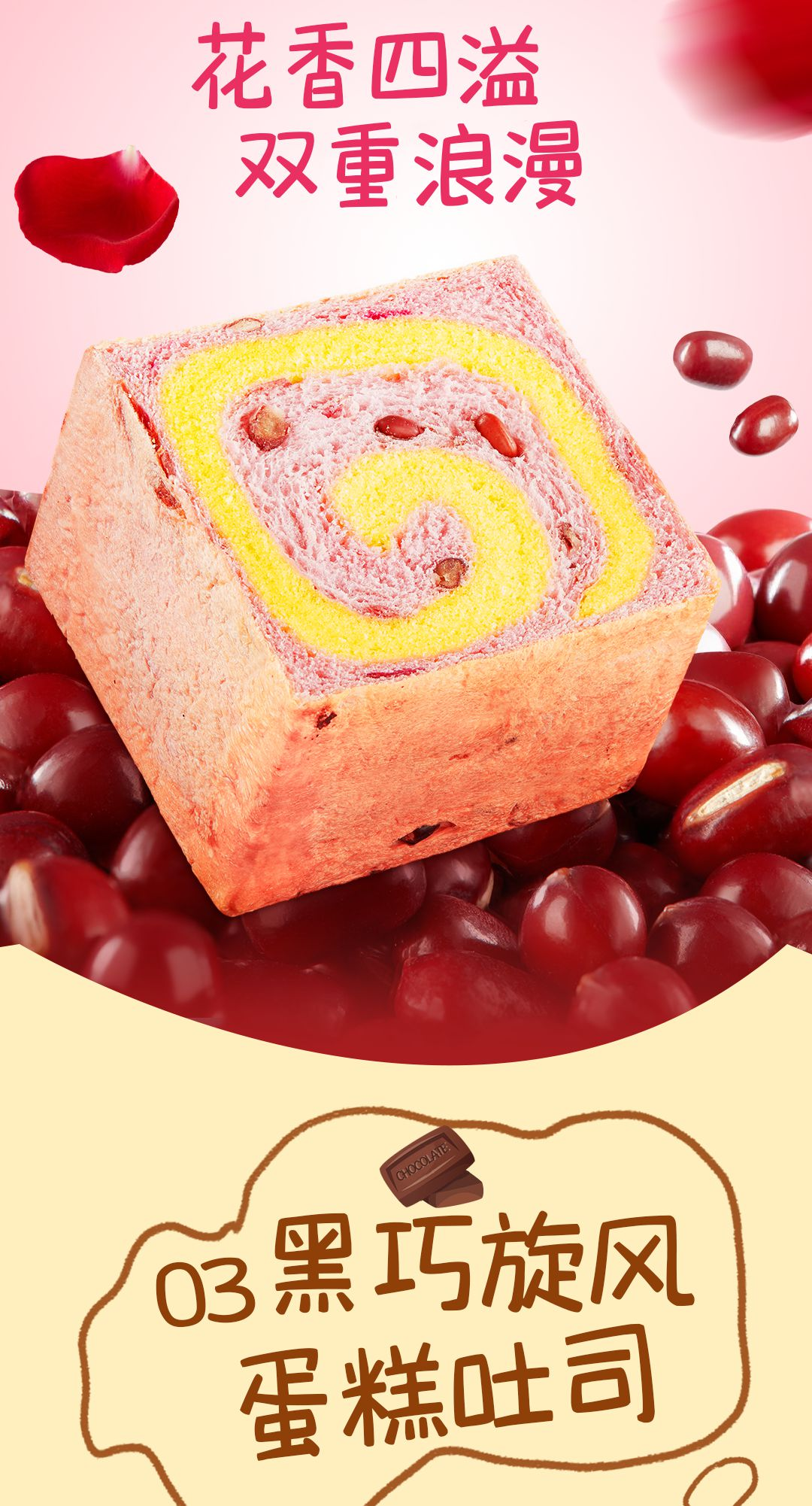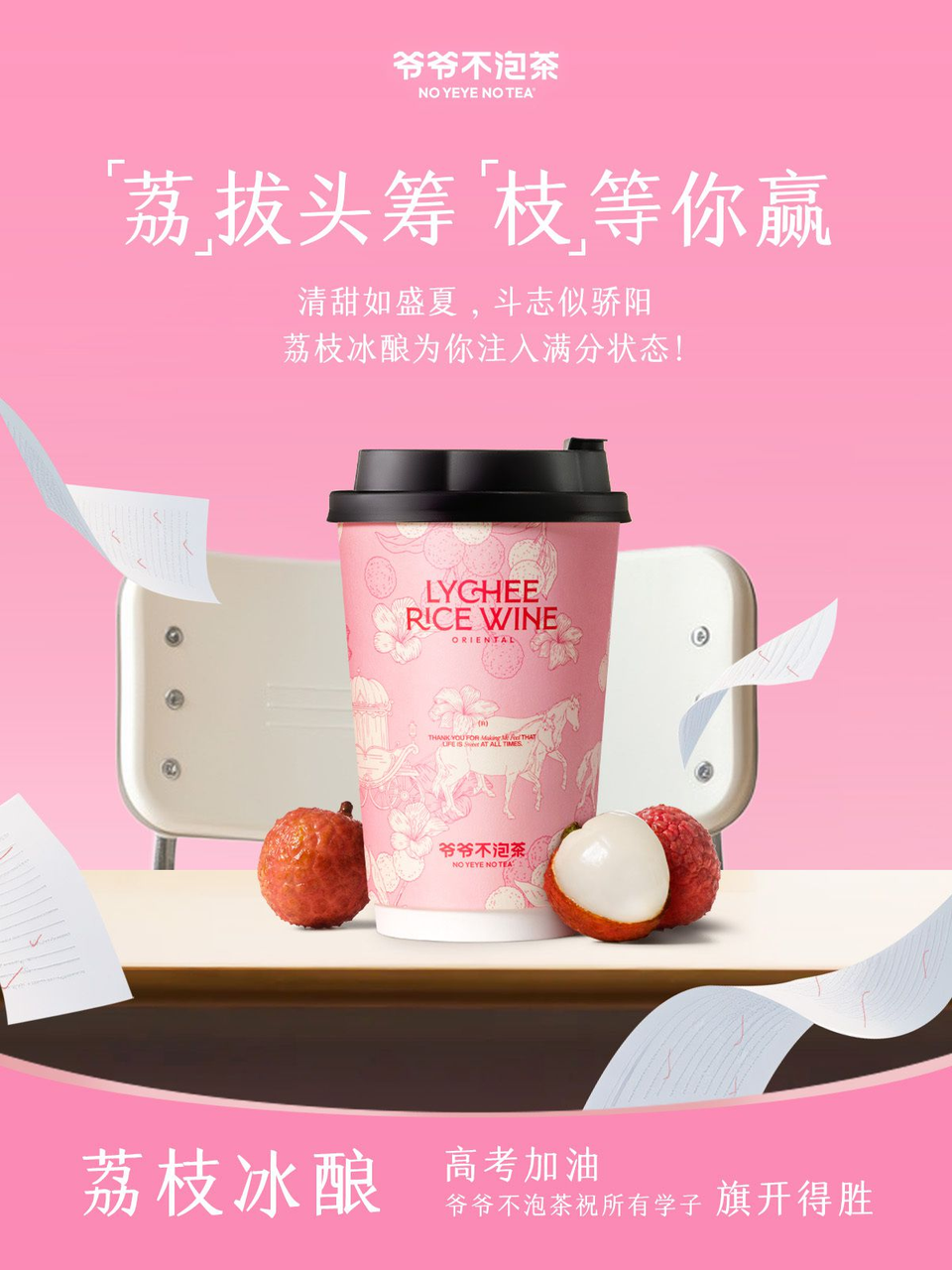
怎么找适合海报的字体?一套方法帮你快速定位
做海报时最让人头疼的问题之一,就是“该用什么字体”。打开字体列表,几百款字体摆在眼前,翻来翻去却不知道选哪个。其实,找对字体并不靠运气,掌握一套方法,就能快速缩小范围、精准定位。
一、先搞清楚:你的海报在“说”什么?
选字体之前,先问自己三个问题:
海报的主题是什么? 是促销活动、品牌宣传、音乐会,还是公益公告?不同主题对字体的要求完全不同。音乐节海报可以用夸张的装饰体,金融讲座海报则需要稳重专业的字体。
目标受众是谁? 年轻人喜欢潮酷、有个性的字体;儿童相关的设计需要圆润可爱的字体;面向高端商务人群,则要选择精致、有质感的字体。
想传递什么情绪? 高端、活泼、复古、科技、温馨还是严肃?字体的情绪必须与海报的整体氛围一致。
这三个问题明确了,选字体的方向就清晰了一大半。
二、认识字体的“性格”
不同字体自带不同的“性格”,选对了能让海报事半功倍:
黑体/无衬线体:简洁有力、现代感强,视觉上自带冲击力,是海报标题的“第一选择”。粗黑体适合促销、公告等需要强烈视觉冲击的场景;细黑体适合科技、互联网等现代感强的设计。代表字体有思源黑体、阿里巴巴普惠体等。
宋体/衬线体:端庄雅致、精致传统,带有文化感和高级感。适合文化艺术、奢侈品、女性行业等追求精致感的设计。
手写体/书法体:个性强、有温度,但辨识度较弱,建议只用于标题,不要用作正文。儿童用品海报适合灵动的手写体;中国风的设计场景,如传统节日、国潮服饰等,书法体是首选。
圆体/卡通体:亲和活泼,适合儿童、少女、甜品等温馨品类。
装饰体/展示体:造型独特、视觉冲击力强,适合音乐节、潮流活动等需要强烈视觉吸引力的场景。同样只适合做标题,不宜用于正文。
三、搭配原则:少即是多
一个海报里字体不要超过2-3种。太多字体会显得杂乱无章,缺乏专业性。
最经典的搭配方式是:一款醒目的标题字体 + 一款易读的正文字体。比如标题用粗黑体,正文用宋体或细黑体。也可以用同一字体家族的不同字重来区分层级——标题用粗体,正文用常规体。
另外,不同字体的调性情绪要保持一致。严肃的宋体不适合搭配活泼的圆体,它们传递的情绪是冲突的。选择字体时,要确保它们“和而不同”——有明显差异,但不违和。
四、免费商用字体推荐
标题用:优设标题黑专为大标题而生,结构严谨、视觉平衡感出色;站酷系列(高端黑、文艺体等)辨识度高,适合传达情感与故事性内容;霞鹜文楷兼具传统书法的灵动与现代字体的规整,适合手写风海报。
正文用:思源黑体字重丰富,Light到Regular适合正文排版,Bold到Heavy适合标题设计;阿里巴巴普惠体适配多场景,免费商用可放心用。
总结
找适合海报的字体,本质上是一个“先定位、再匹配”的过程。先明确海报的主题、受众和情绪,然后根据字体的“性格”选择合适的类别,最后在同类字体中筛选出具体的一款。掌握这套方法,你就不再需要从几百款字体里大海捞针了。